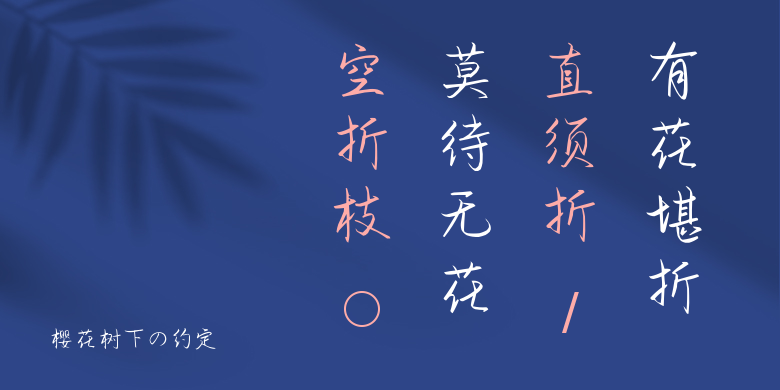
樱花树下の约定
樱花树下の约定,这款字体结构工整、笔画清晰,兼顾美观与易读性,适用于标题、正文、海报、包装、LOGO 等多种场景。字形优雅稳定,风格百搭耐看,适配日常排版与创意设计,让文字呈现更舒适、更具质感。樱花树下の约定一笔一画,皆是细节,以均衡的比例、流畅的线条打造舒适视觉体验,字形端正大气,风格简约现代。无论是商业设计、品牌宣传还是日常排版,都能轻松驾驭,让文字更有格调与力量。樱花树下の约定字体下载。